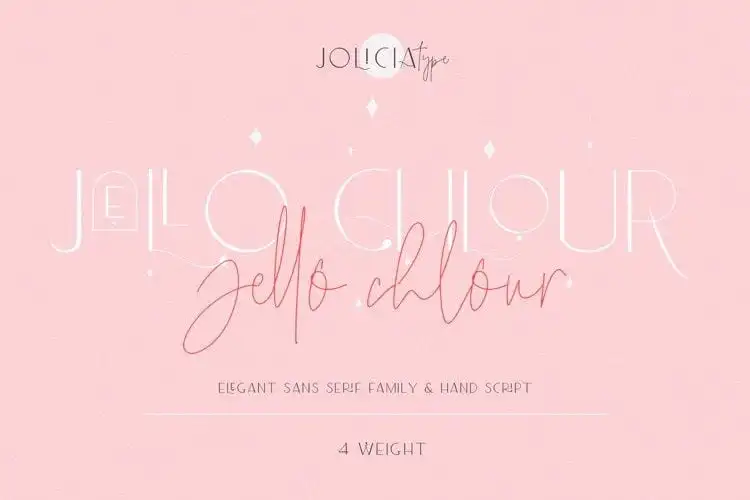
Jello Chlour Sans Serif Font – Download Grátis
A Jello Chlour Sans Serif é uma fonte moderna e elegante, perfeita para criar logotipos únicos e belos. Com seu estilo único que inclui ligaturas padrão, ela se destaca como um recurso versátil para designers de diferentes níveis. O design da fonte suporta múltiplas línguas e todas as ligações incrivelmente bonitas em seus vários formatos se ativam automaticamente, permitindo que você utilize esses detalhes sem a necessidade de programas especializados. Esta font é uma ótima opção para estilizar qualquer layout da revista ou para criar gráficos que precisem de um visual moderno com um ar elegante. Seja para seu próximo projeto editorial ou trabalho gráfico, a Jello Chlour Sans Serif é uma escolha perfeita.